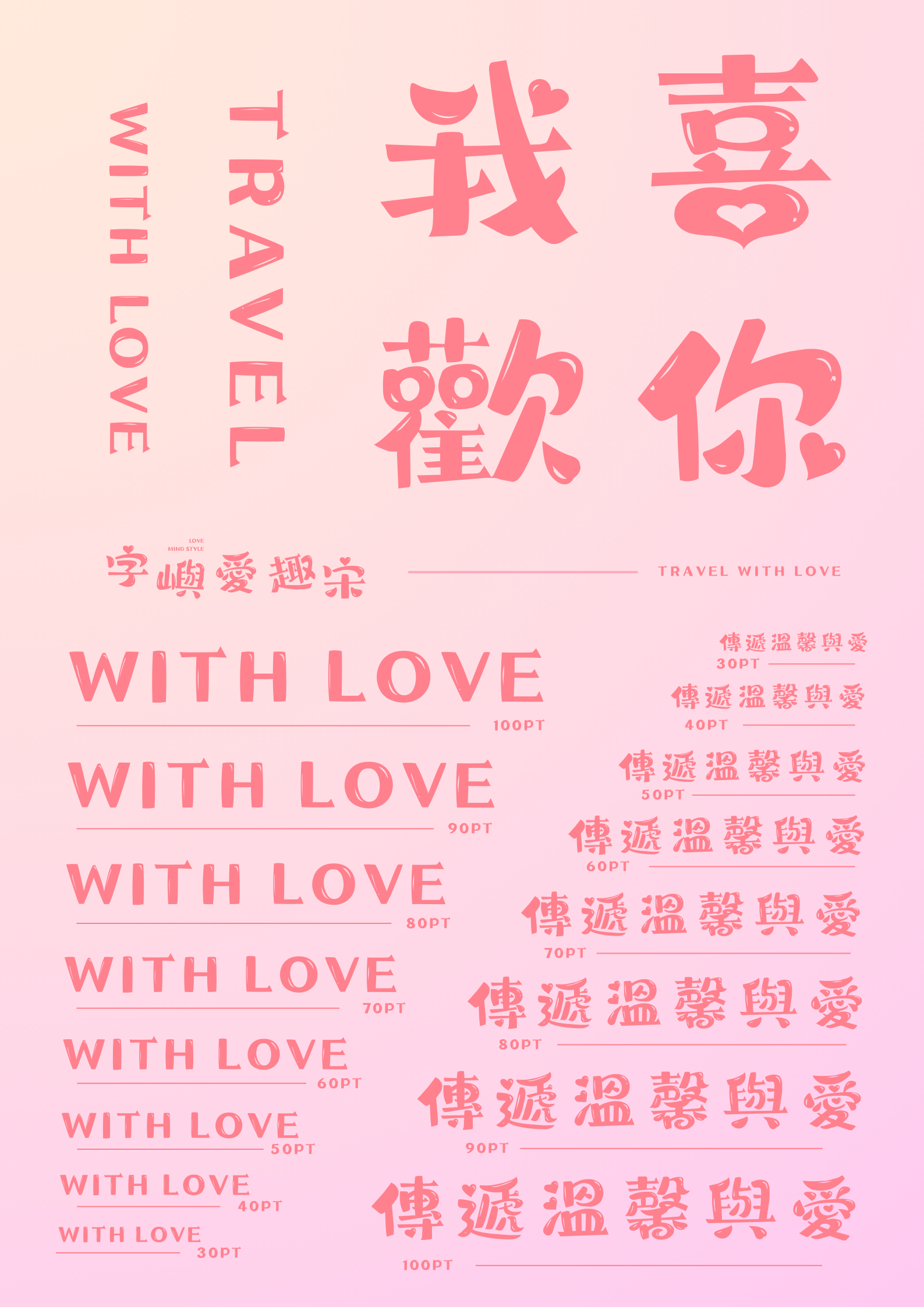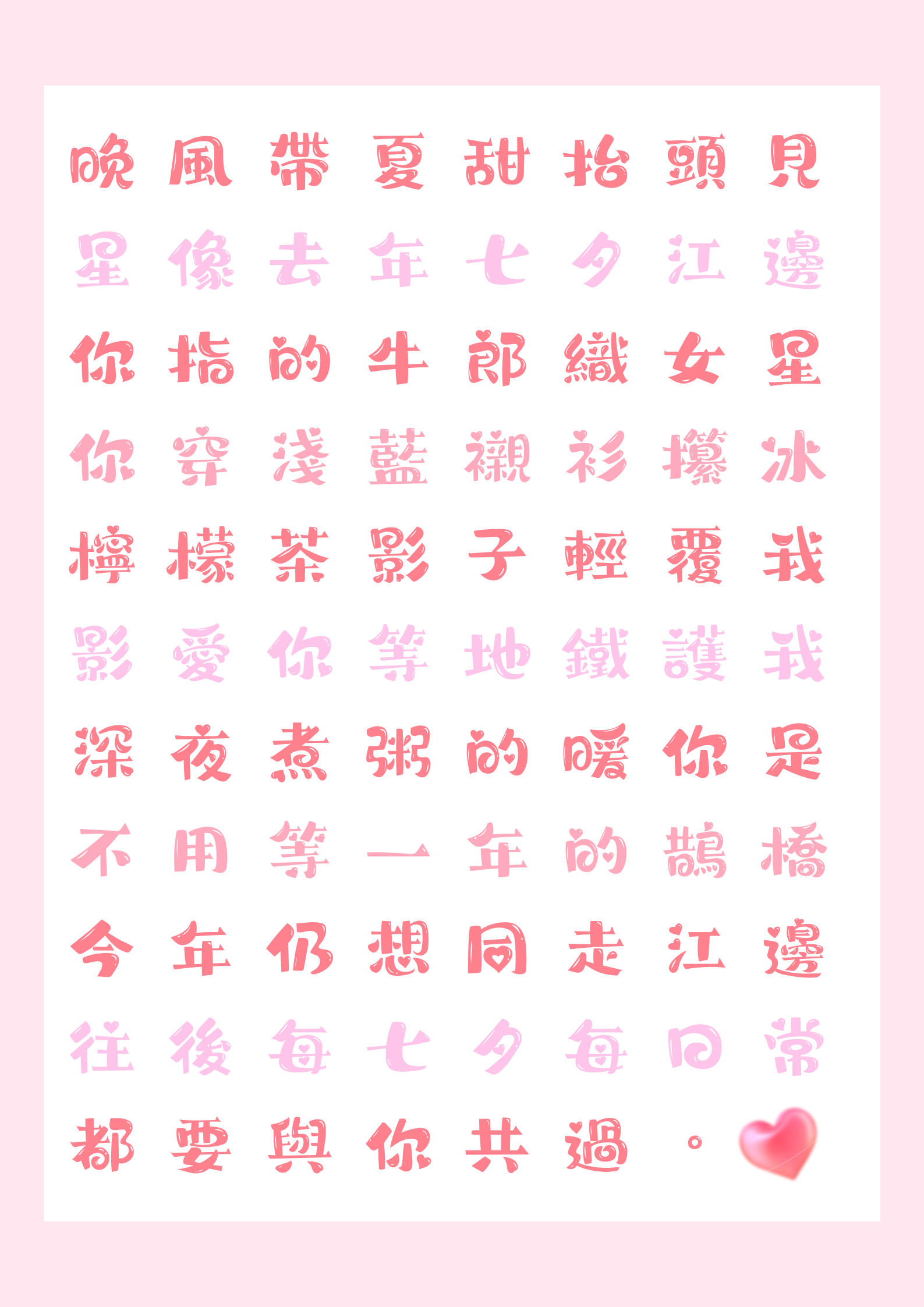
字嶼愛趣宋TC
字嶼愛趣宋 TC:讓文字滿載愛心,可愛設計必備字體!
還在找一款能傳達溫馨感的字體嗎?看看「字嶼愛趣宋 TC」吧!這款看似帶有宋體輪廓的字型,藏著滿滿的可愛巧思 —— 設計師把部分筆劃變成了愛心形狀,讓每個字都像在對你比心,不管是做海報、包裝還是社群貼文,都能瞬間溫暖人心!
突破傳統的可愛魔法:宋體也能這麼萌!
愛心筆劃藏驚喜:「心」字的點直接變成一顆小愛心,「愛」字的撇畫末端翹起愛心尾巴,就連「笑」字都藏著迷你愛心,每個字都像手繪般充滿溫度,比普通宋體多了份療癒感。
圓潤線條減齡感:保留宋體的基本架構,把直角改成圓弧,橫豎筆劃粗細對比柔和,看起來像棉花糖一樣軟萌,就像把傳統宋體穿上了可愛外套。
細節藏著巧思:比如「口」字框的線條微微彎曲,不會死板,讓文字有了呼吸感。
5 大暖心場景,哪裡需要愛心就去哪!
不管是甜點包裝還是節慶卡片,這款字體都能讓設計瞬間加分:
親子與兒童領域:孩子一看就喜歡
幼稚園的活動海報寫「歡迎入園」,兒童繪本的標題用「故事時間」,甚至寶寶的成長手冊封面,用它來裝飾都超合適!字嶼愛趣宋 TC 能讓孩子們主動盯著文字看。
甜點與飲品:讓美味更有儀式感
蛋糕盒上的「生日快樂」、奶茶杯的「甜度剛好」、手工餅乾的「暖心小點」,用這款字體印上去,甜點看起來更可口!
社群與網路:貼文互動率偷偷漲
IG 限動分享「今日甜點」、FB 貼文標「寵粉福利」、YouTube 影片標題寫「療癒時光」,愛心字體在小螢幕上超吸睛,粉絲忍不住留言「字體好可愛!」,互動率比用思源黑體時高了不少。
節慶與禮物:心意藏在字裡行間
情人節卡片寫「我愛你」、母親節禮盒標「謝謝媽媽」、兒童節邀請函印「一起玩耍」,愛心筆劃替你說出暖心話,不用額外畫插圖就充滿儀式感,收到的人肯定能感受到滿滿誠意。
文創與周邊:小物也能變成搶手貨
手帳貼紙印「加油」、帆布袋印「天天開心」、手機殼刻「平安喜樂」,用這款字體做設計,小物件也能變得獨一無二。很多文創市集的攤主都說,換了這款字體後,商品賣得更快了!
標準字集:自由創作,靈活應用
字嶼愛趣宋 TC 以臺灣常用標准字集為標准,參考jf7000字集,包括注音符號、英文字母、阿拉伯數字和標點符號,約7640字以上。涵蓋了日常生活和設計中常用的漢字、字母、數字以及各類標點符號,支援大多數使用情境。
無論是面向大眾的設計作品,還是涉及到國際交流、英文元素的設計專案,字嶼新魏體 TC 都能提供支援。(目前字集先以臺灣常用標準字為基礎建置,後續會逐步規劃擴充在地化用字,期待未來能更完整地服務書寫需求。)在處理英文單詞或數字信息時,其字母和數字的設計與漢字相互呼應,保證了整體排版的和諧統一。讓設計師在創作過程中可以更加專注於發揮創意,靈活地運用這款字體打造出各種獨具匠心的作品。
字嶼愛趣宋 TC 字體以其融合古典與趣味的獨特風格、廣泛的適用場景、豐富的字元資源以及嚴格的版權保護,成為字體設計領域中備受矚目的一款字體。它猶如一座連接古典與現代的橋樑,用獨特的魅力為各類設計作品注入了新的活力,幫助設計師們將創意完美地呈現出來。無論您是專業的設計師,還是有設計需求的企業或個人,字嶼愛趣宋 TC 字體都可能是您在追求兼具文化底蘊與趣味創新設計時的理想選擇,讓您的作品在眾多信息中脫穎而出,吸引更多目光,傳遞出獨特的文化與藝術魅力。